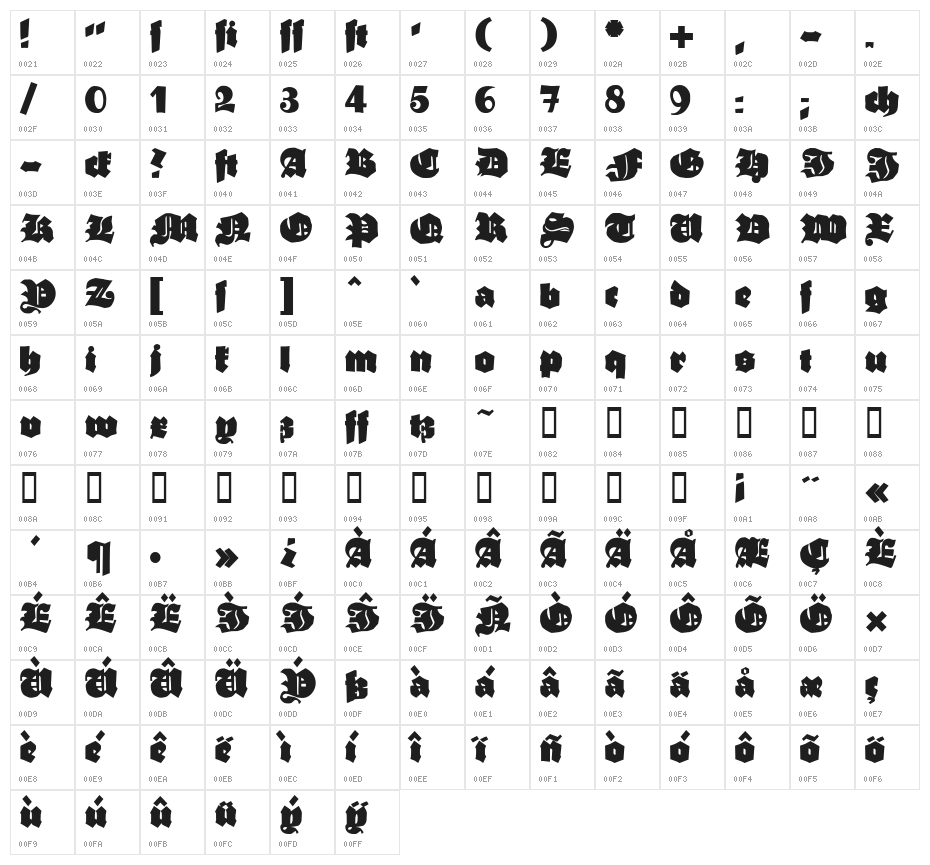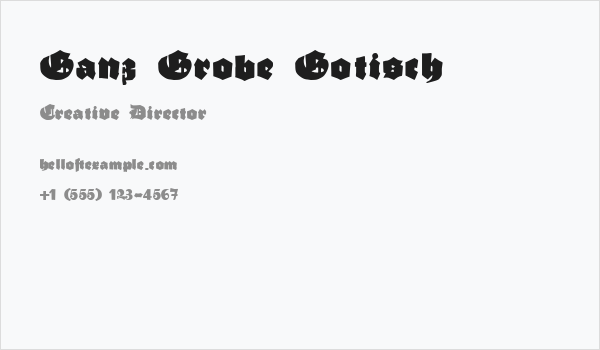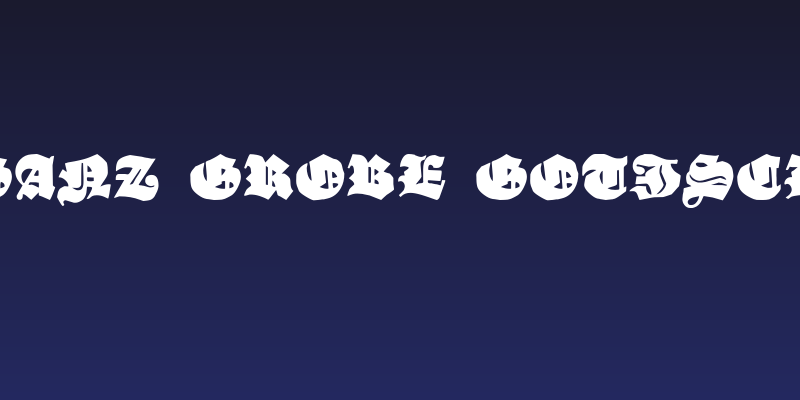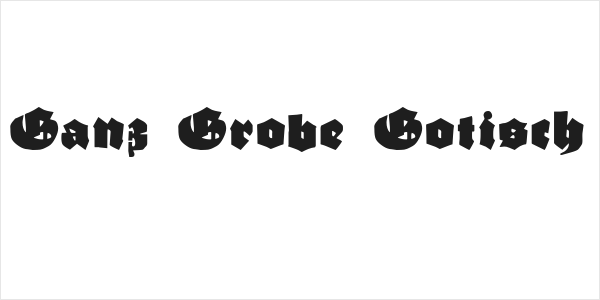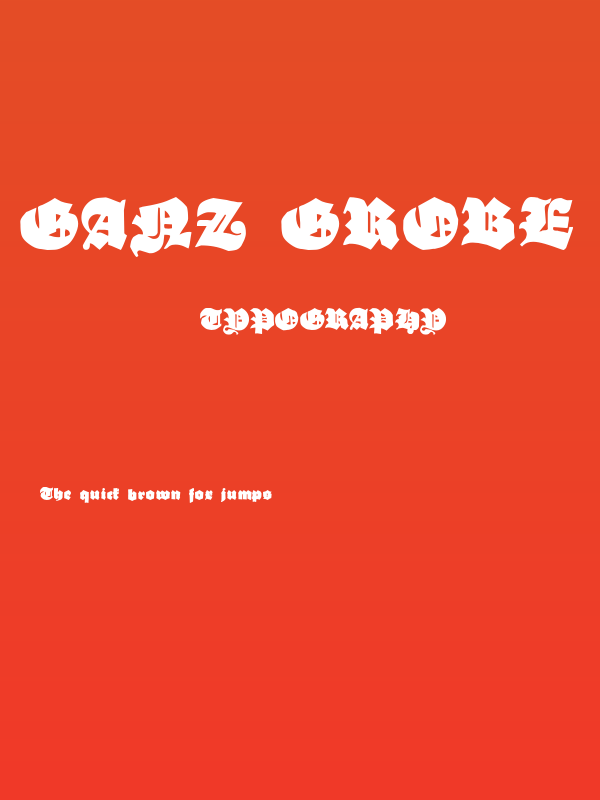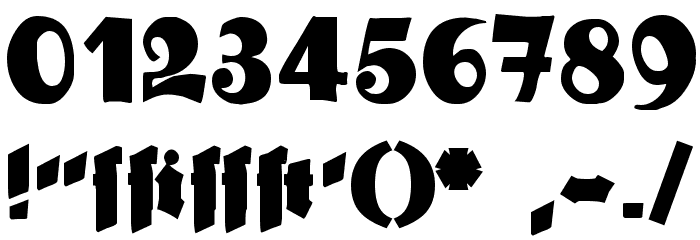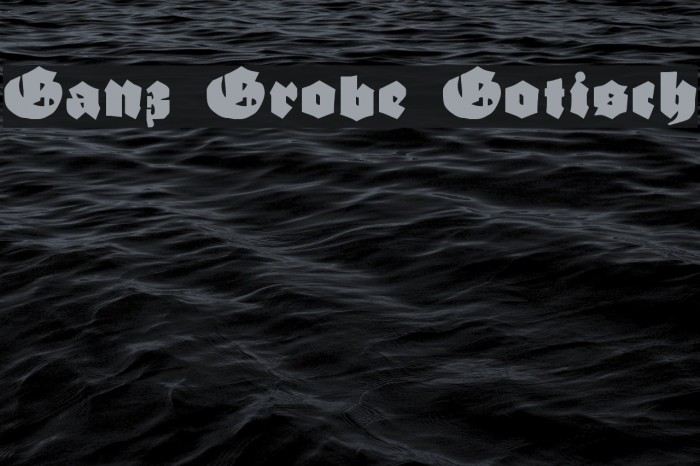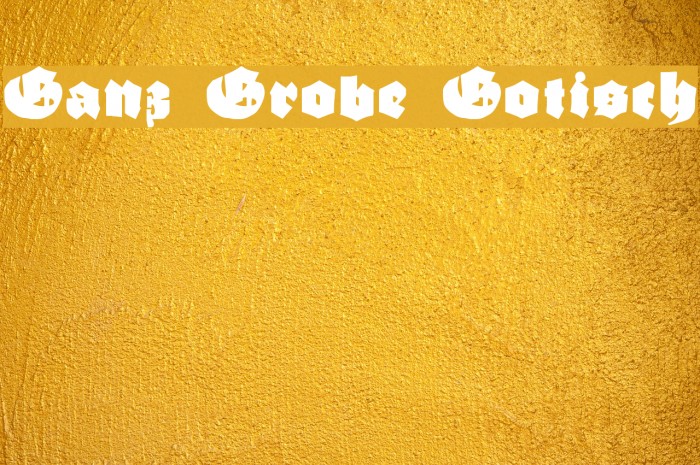
Ganz Grobe Gotisch Font
| Cas d'utilisation | Logos, Headlines, Decorative text |
| Projets proposés | Suitable for historical themed designs, book covers, posters, and branding that requires a vintage or medieval touch. |